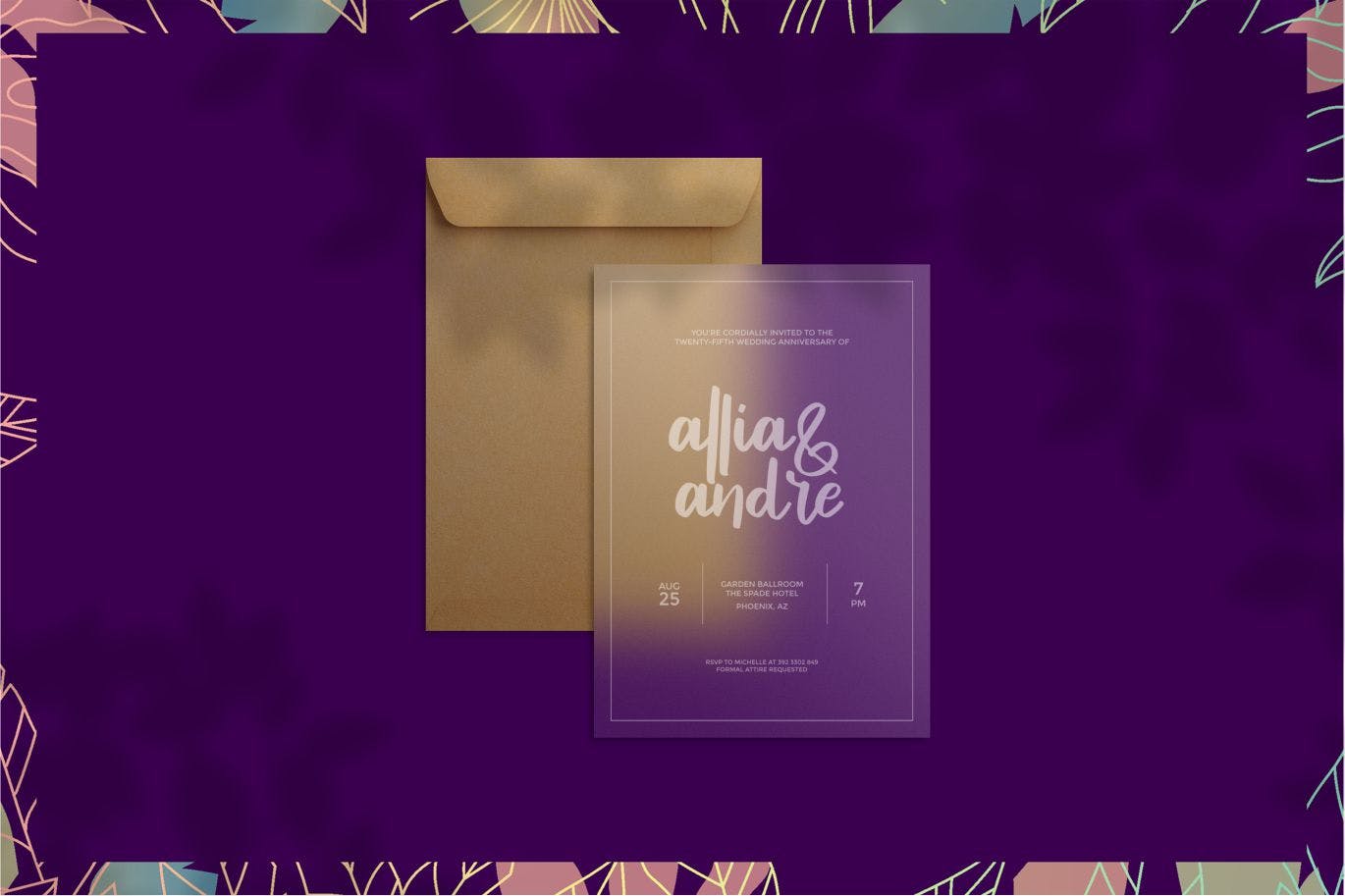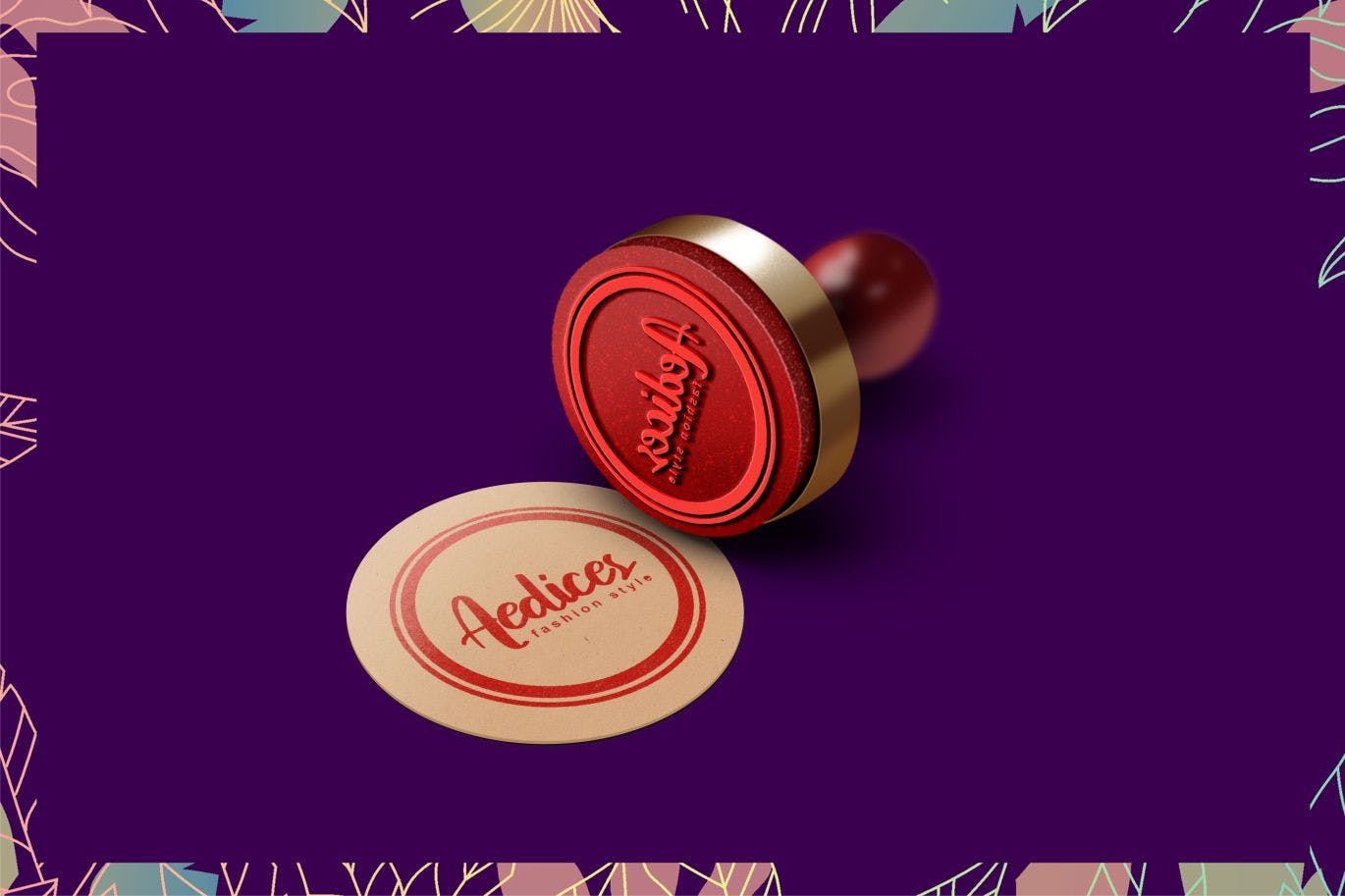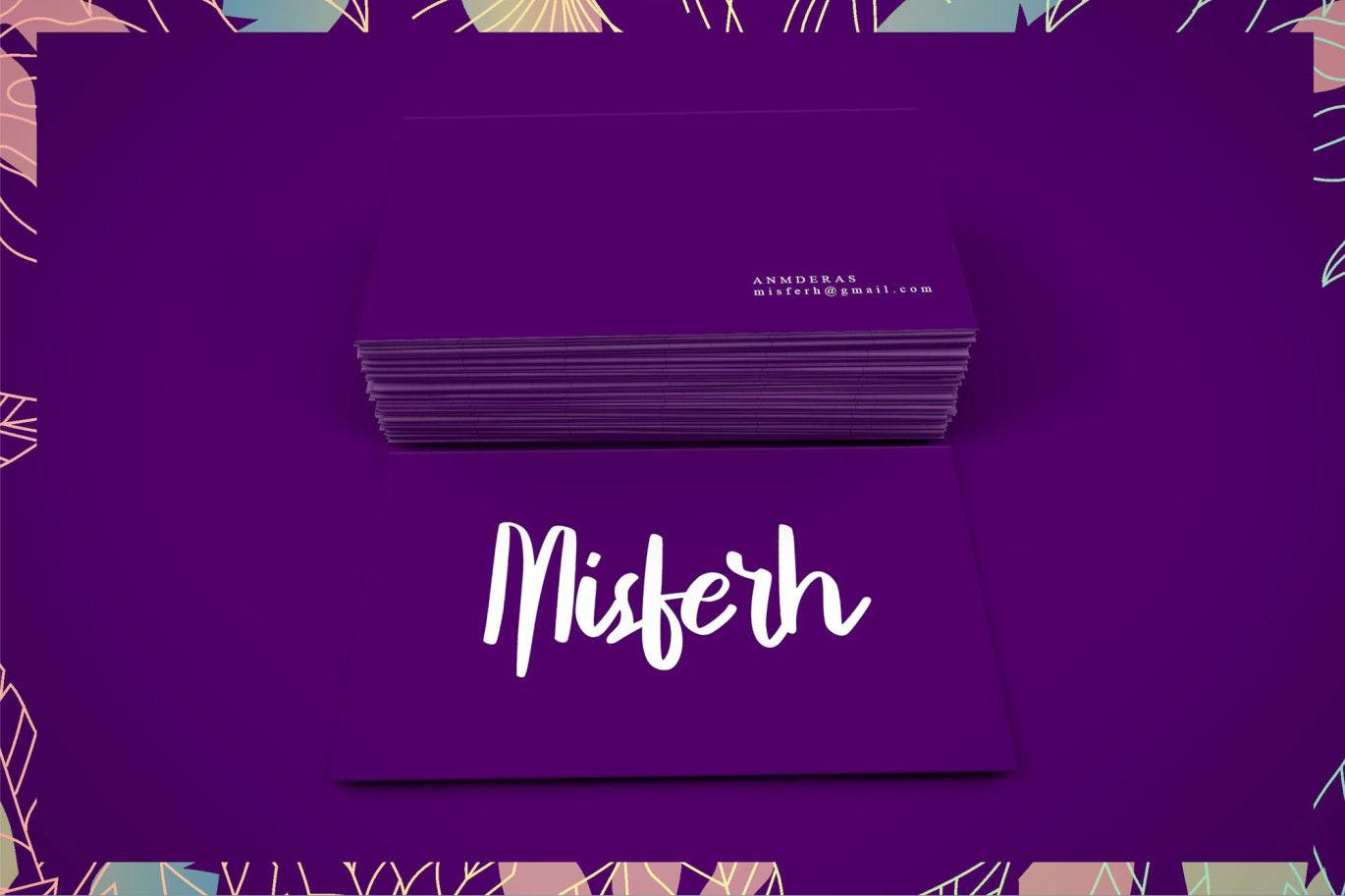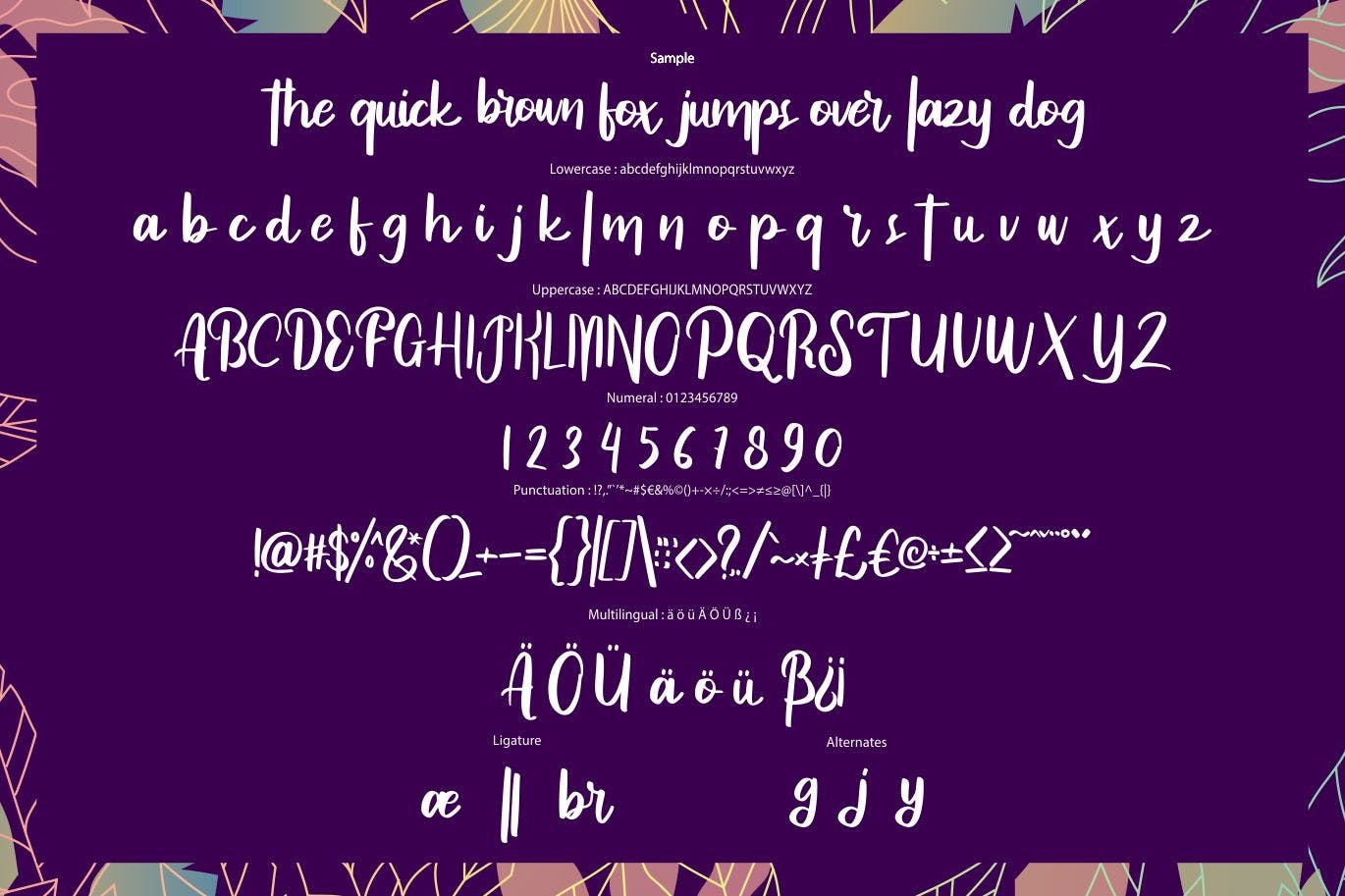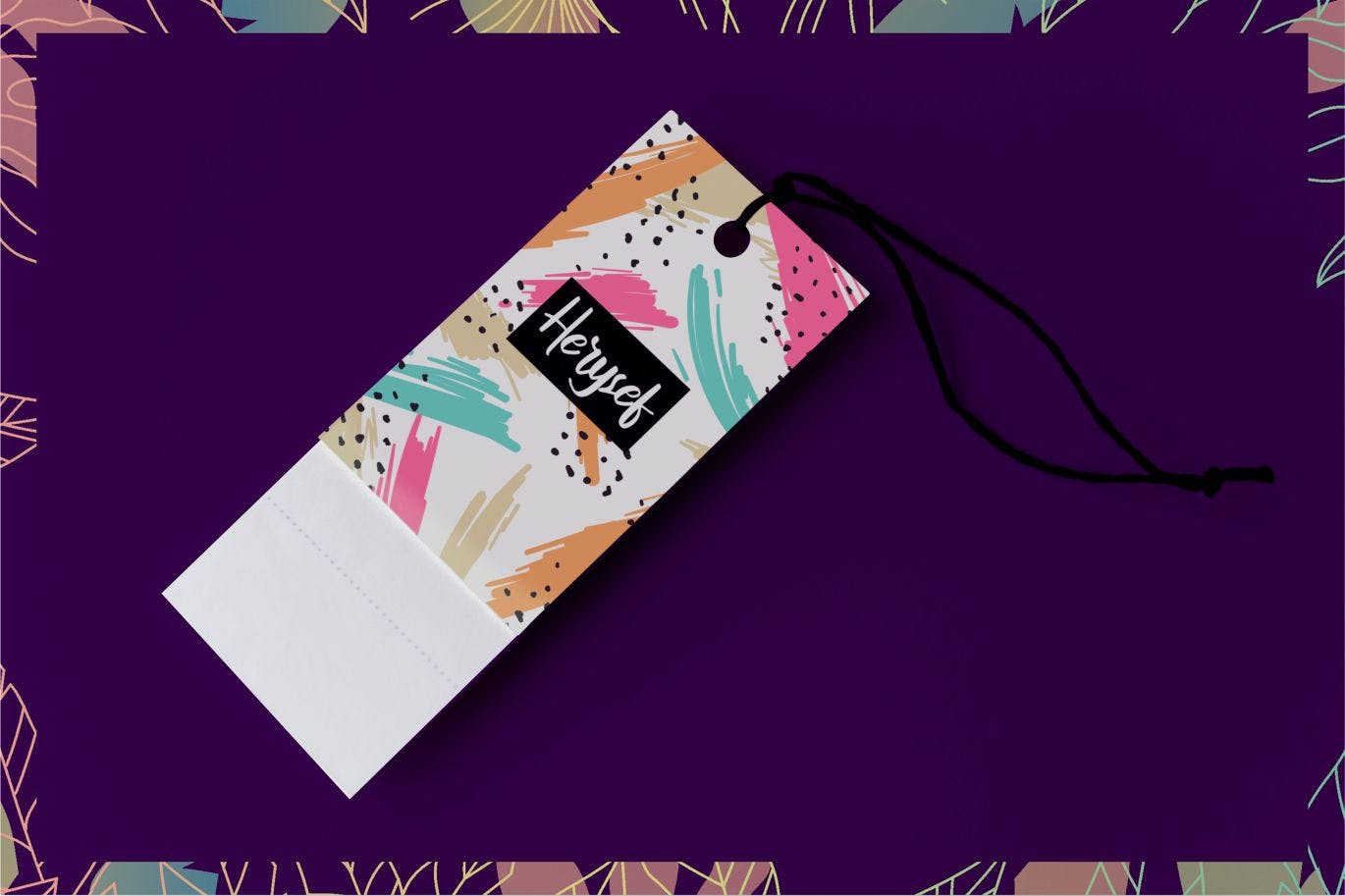
Nebreta | فونت مدرن خطی با سبک خوشنویسی، بسیار زیبا برای دعوتنامهها، کارتهای تبریک، مواد برندینگ، کارتهای کسب و کار، نقل قولها، پوسترها و بیشتر!
کاراکترهای جایگزین به چندین ویژگی Open Type تقسیمبندی شدهاند، مانند مجموعههای استایلیستیک، جایگزینهای استایلی، جایگزینهای متنی، SWASH و لیگاتورها. ویژگیهای Open Type را میتوان با استفاده از برنامههای حرفهای مانند Adobe Illustrator، Adobe InDesign، Adobe Photoshop، Corel Draw X و Microsoft Word دستیابی کرد. این فونت دارای کدگذاری PUA یونیکد است (فونتهای بهطور خاص کدگذاری شده) که امکان دسترسی آسان به تمامی کاراکترهای جایگزین را فراهم میکند.